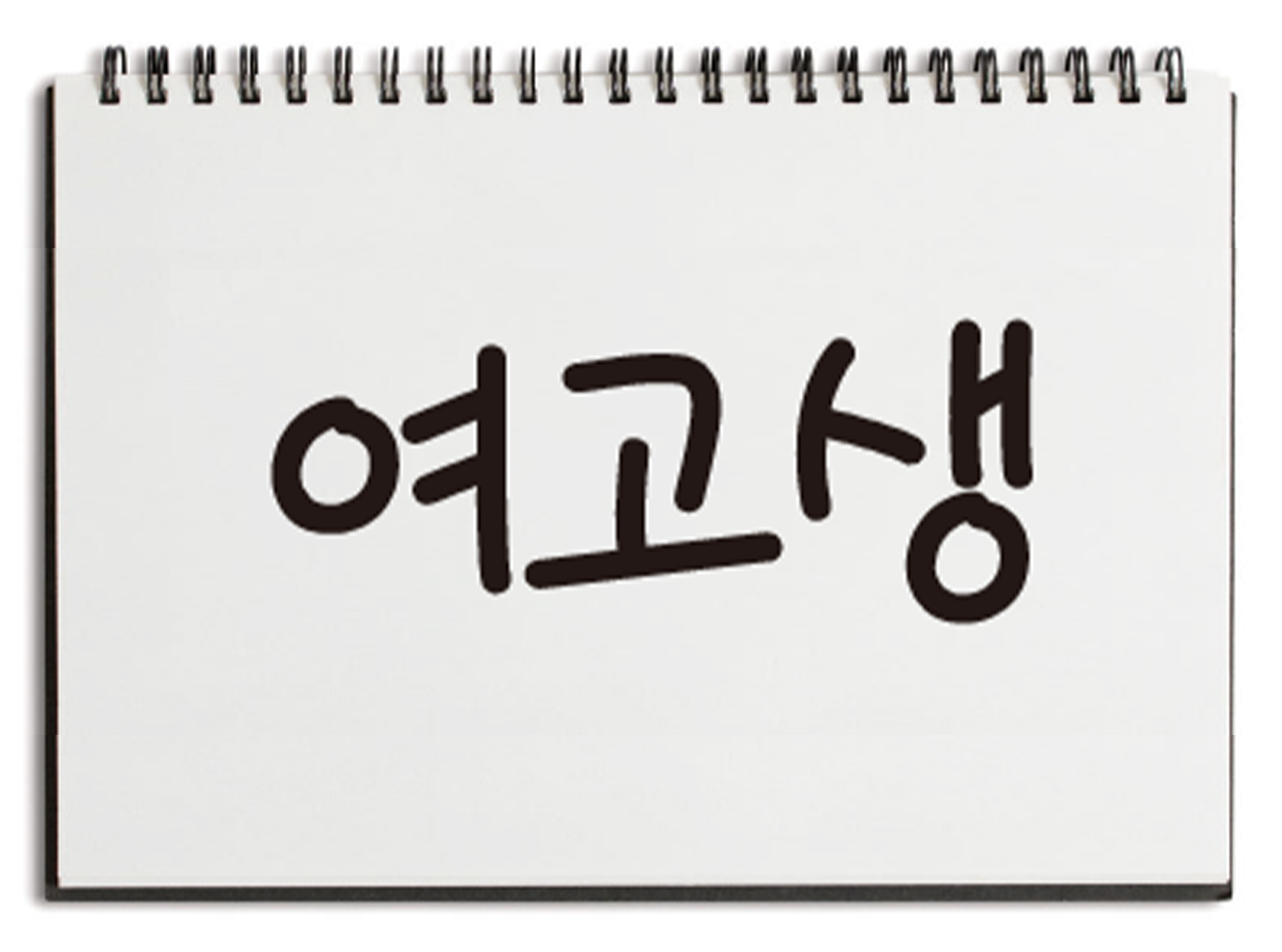
폰트      HU여고생
굵기      2종
기간      2012
구성      KS한글 2,350자
수업시간에 공책에 필기하는 여고생의 글씨체 느낌을 살린 서체입니다.
HU여고생120
오랫동안 꿈을 그리는 사람은 마침내 그 꿈을 닮아간다.
HU여고생140
오랫동안 꿈을 그리는 사람은 마침내 그 꿈을 닮아간다.